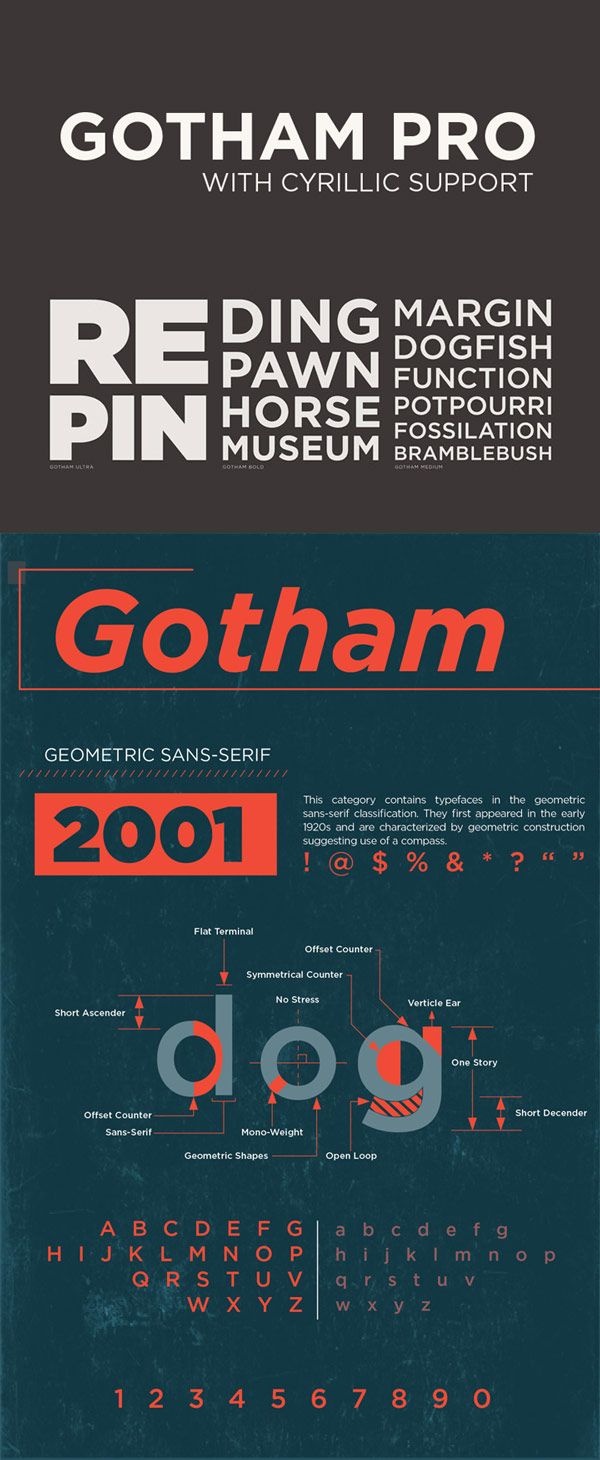
10 бесплатных альтернатив шрифтов к Gotham
Типичный шрифт Gotham является одним из самых популярных без засечек в обращении. Созданный на рубеже тысячелетий Тобиасом Фрере-Джонсом для литейного цеха Hoefler & Co., он основан на основных формах письма, которые Фрер-Джонс видел в зданиях вокруг Манхэттена, в вывесках и архитектурных надписях.
Квинтэссенция американского чувства в дизайне привела к использованию шрифтов в бесчисленных проектах брендинга — президентской кампании Барака Обамы, Национальной мемориалу и музею 11 сентября и Saturday Night Live, а также многих других фамилиях приняли Gotham.
Описанный Hoefler & Co. просто как «Какие буквы похожи», это современность, честность и уверенность шрифта, которые делают его настолько популярным.
1. Монсеррат
Дизайнер Джульетта Улановский назвала Монсеррат по соседству в Буэнос-Айресе, в котором она работает. Он был вдохновлен местными архитектурными вывесками так же, как и Готам. Меньше более широкие буквы Монтсеррата дают расслабленное ощущение, что Готэм не может собрать.
2. Nexa
Nexa Light и Nexa Bold доступны для скачивания бесплатно. Они немного более выразительны, чем некоторые шрифты в этом списке, в частности строчные буквы g и верхний регистр J и Q. Большая часть базовой формы вдохновлена Gotham, а Nexa отлично подходит для брендинговых проектов.
3. Pier Sans
«Пьер Санс» Матье Дежардинс — бесплатный шрифт с 10 стилями. Подобно геометрическим для Готэма, Пирс Санс толкает 1930-е годы немного дальше. Возможно, это больше Майами, чем Манхэттен.
4. Raleway
Raleway — это всеобъемлющий геометрический sans-serif в 18 шрифтах. Вес варьируется от тонкого до черного, и каждый вес имеет сопроводительный курсив. Предназначен для использования при размерах дисплея, он близок к Gotham многими способами, с очевидным исключением позвоночника на S.
5. Видение
Vision — это целая семья из 12 шрифтов, бесплатно для коммерческой и некоммерческой работы. Дробь, более гуманистическая, что Готэм, особенно в нижнем регистре, Видение использует те же основные буквенные формы со слегка более узким, менее округлым скелетом.
6. Museo Sans
Если Gotham чрезмерно используется, это лишь незначительно больше злоупотребляет, чем следующий шрифт в нашем списке. Museo Sans чрезвычайно популярен среди веб-дизайнеров, потому что он предлагает такую же эстетику, ни для чего.
7. Gothvetica
Gothvetica: Gotham, смешанный с Helvetica. Это своего рода mashup, который кажется только стоящим начинанием, когда дизайнеры моделей собираются вместе для одного слишком большого количества напитков. Но как-то это работает. Это забавный проект, бесплатный для некоммерческой работы.
8. Готический A1
Gotham понятен американец, учитывая его корни в архитектурной идентичности Нью-Йорка, но популярность его простого модернизма простирается далеко за пределы Америки. Gothic A1 — бесплатный без засечек с похожим чувством, но с широкой поддержкой корейских, а также латинских символов.
9. Kiona
Kiona — это минимальный геометрический шрифт в верхнем регистре, который похож на Gotham во многих его персонажах. Но Киона подчеркивает диагональ в своем отличном K, а R. Kiona светлые, полужирные и полужирные — все премиальные шрифты. Kiona регулярно можно скачать.
10. Бухты
Coves — это простой геометрический sans-serif, который разделяет большую часть своей ДНК с Gotham, вершиной на M, отсутствием поперечной балки на J, формой двойной высоты a, все идут по одной и той же схеме , Это бесплатно для личного использования, но для коммерческого использования вам понадобится лицензия.
Бонус: 5 премиальных шрифтов Альтернативы Gotham
Огромный объем работы, связанной с проектированием полного семейства шрифтов, означает, что когда шрифты — это труд любви, они обычно фокусируются на нескольких ключевых весах или стилях. Обычно вы получите регулярный и смелый, но не курсивный. Исключением является то, что проект берется сообществом добровольцев, таких как команда за Монтсерратом, когда он способен вырасти в более широкий набор шрифтов.
Вот пять премиальных альтернатив Gotham, для тех, кому требуется немного больше гибкости.
11. Мэллори